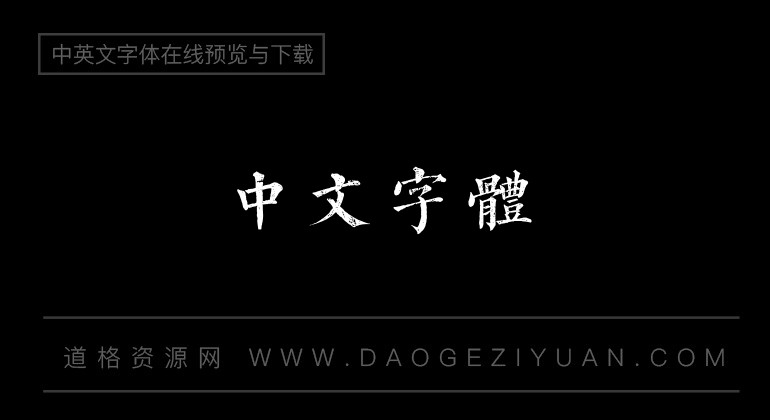
字酷堂石刻体
字酷堂石刻体是一款精美的石刻字体,由字酷堂设计师潘静绘制,它采用细腻的笔触,给人以古朴典雅的感觉,展现出一种历史悠久的气息。字酷堂石刻体采用精致的线条,每一个字都经过精心设计,充满了文化气息,有着明显的石刻风格。字酷堂石刻体具有良好的可读性,适合用于印刷出版、网页设计、平面设计等方面。
字酷堂石刻体是一款非常不错的手写艺术字体,具有很好的视觉感,适合于文化类的宣传设计、商业类品牌的广告和产品包装设计以及个性化文字排版等较多场景。
字酷堂石刻体字符映射图